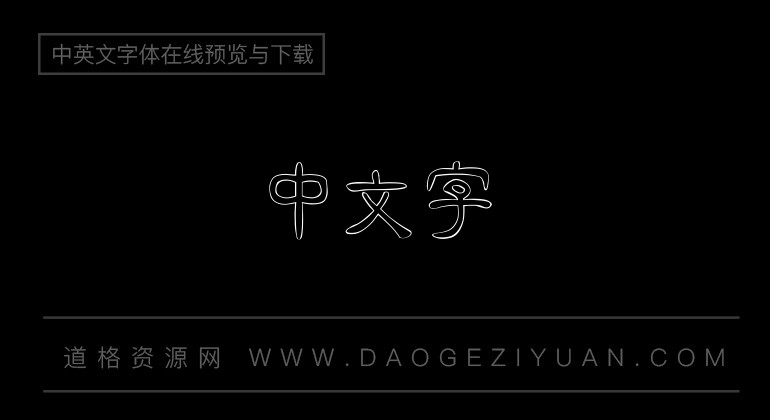
金梅中隶空心国际码
金梅中隶空心国际码是一种简洁、优雅的字体,它以现代风格为主,极具现代感。金梅中隶空心国际码字体的特点是字母细节较少,线条简洁,没有多余的装饰,给人以时尚、简洁、优雅的感觉。它适合用于报刊、广告、商标等设计领域,也可以用于网页、桌面软件、游戏等软件的界面设计。
金梅中隶空心国际码是一款非常不错的手写艺术字体,具有很好的视觉感,适合于文化类的宣传设计、商业类品牌的广告和产品包装设计以及个性化文字排版等较多场景。